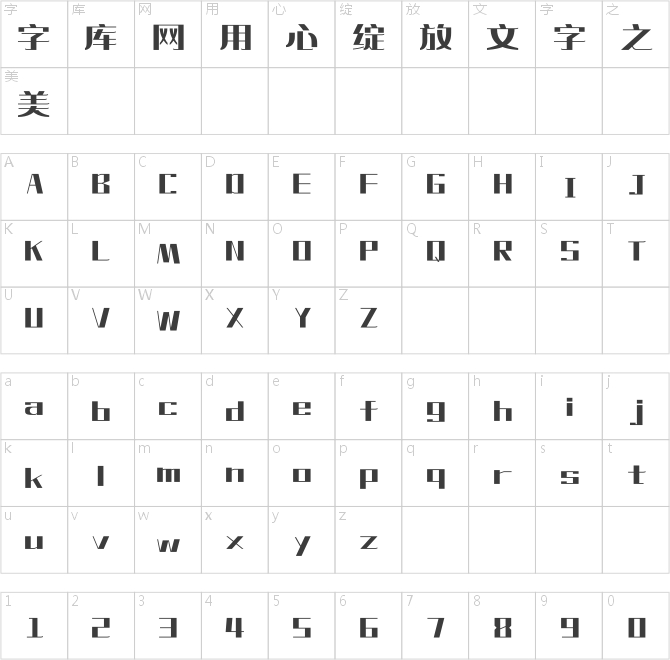
上首言黑體,字體字形風(fēng)格典雅,橫豎筆畫(huà)對(duì)比強(qiáng)烈,特點(diǎn)十分鮮明。適用于搭配標(biāo)志、廣告標(biāo)語(yǔ)、商業(yè)廣告等高端屬性。
上首言黑體字體字庫(kù)是一款讓人賞心悅目、百看不厭的中文字體,適合各類廣告和產(chǎn)品包裝設(shè)計(jì)應(yīng)用,字體大小2.22MB,格式為ttf字體,上傳用戶是上首造字,作者/版權(quán)方為上首造字